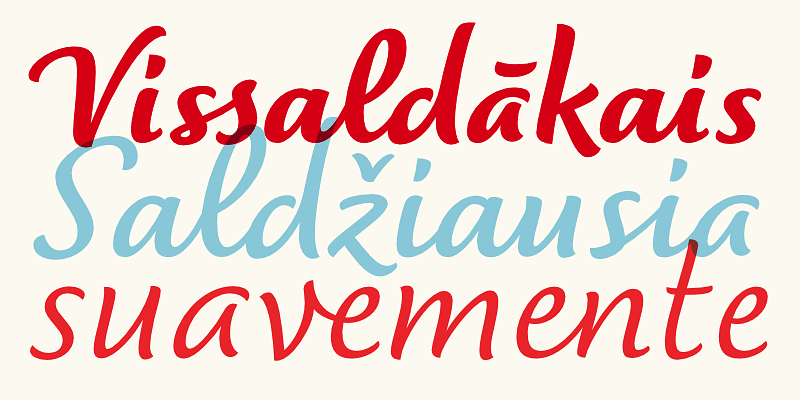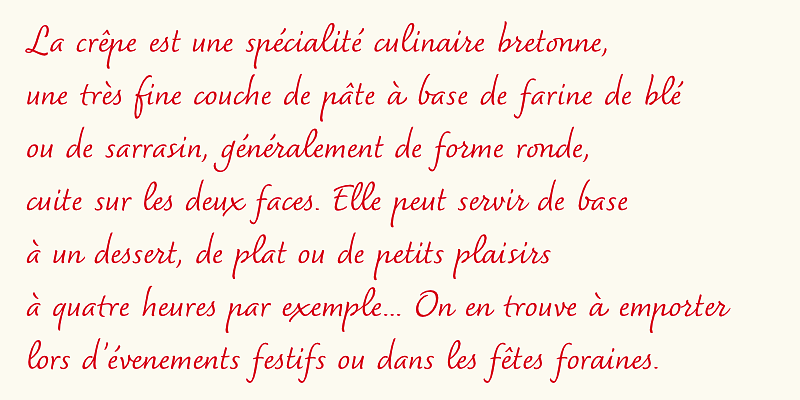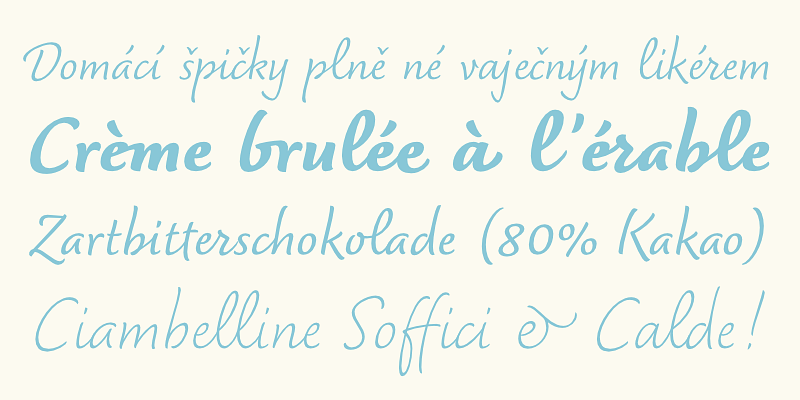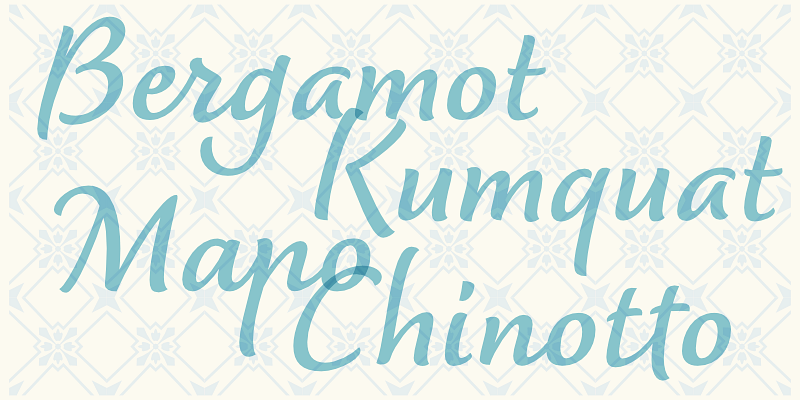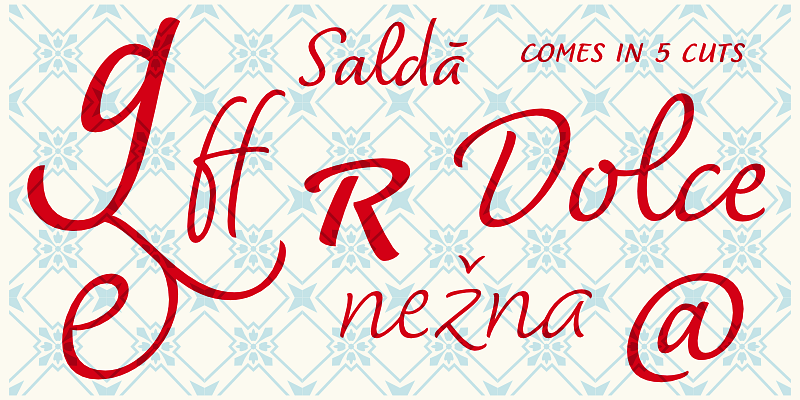
Dolce trova un equilibrio tra l’ordinato e l’informale, risultando in un tipo di scrittura che scorre con naturalezza. Il maiuscoletto è incluso per l’impostazione di tutto maiuscolo, oltre a un ampio supporto linguistico.
La libreria di caratteri tipografici spazia da Dolce, un pluripremiato carattere script, a DejaRip, un sans serif funzionale progettato per dispositivi elettronici e web design, ad Acuta, una famiglia serif multiuso, contemporanea e robusta.